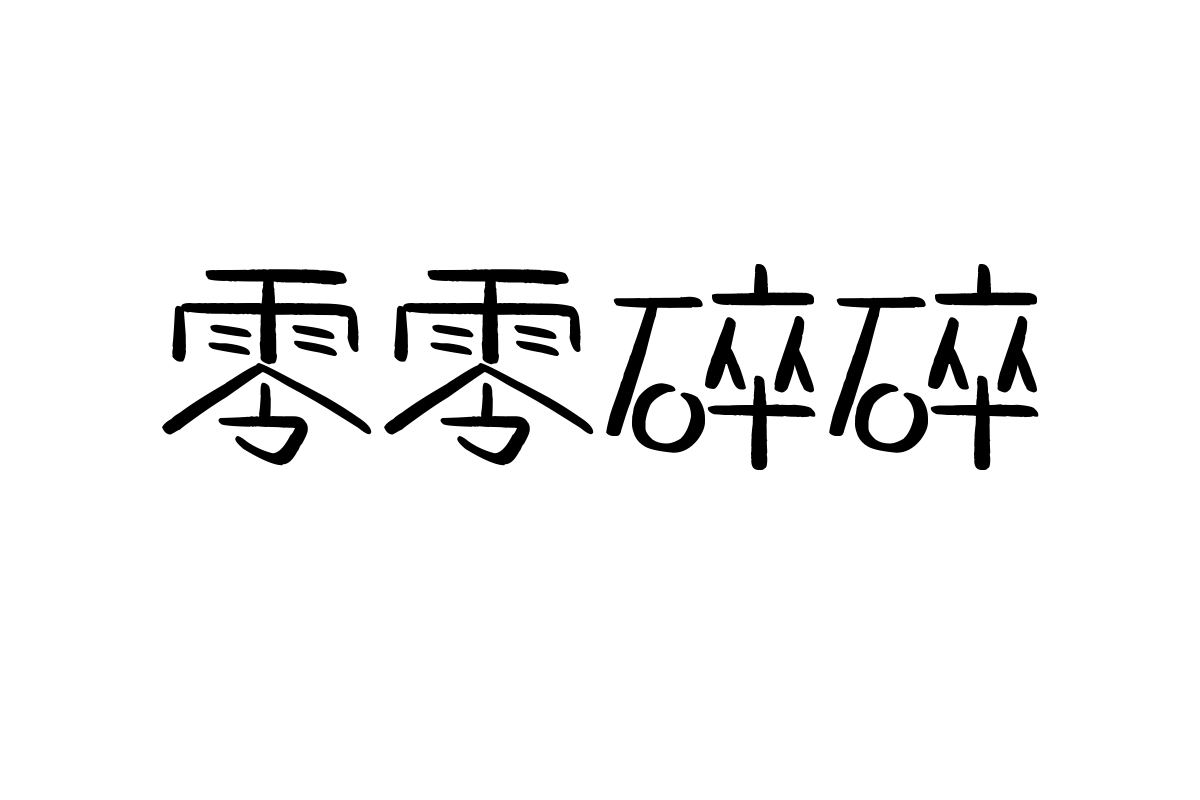
造字工房简言体是一款由造字工房团队开发的免费开源字体,旨在为用户提供一种简洁、易读的中文字体体验。这款字体采用了现代设计元素,结合了传统汉字的特点,使得字体既具有美感又不失实用性。
造字工房简言体的主要特点如下:
1. 简洁明了:该字体采用简约的设计,字形清晰,易于辨识,适合用于各种应用场景,如书籍、杂志、网页等。
2. 易读性高:字体结构紧凑,笔画简洁,使得阅读起来更加轻松,提高了文字的可读性。
5. 适用于多种场景:无论是在印刷品、广告、海报、名片还是网站设计中,造字工房简言体都能够满足用户的需求,提供良好的视觉效果。